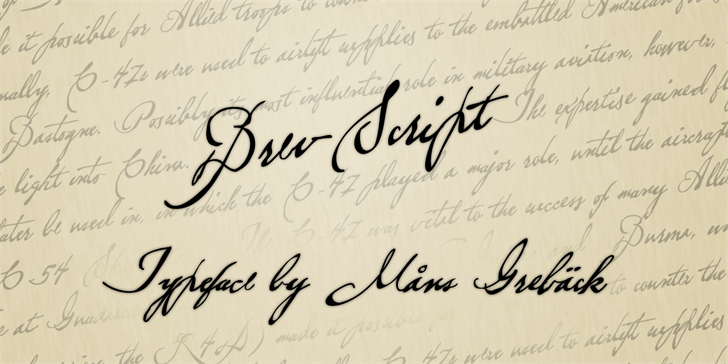
Brev Script font – Download Grátis
A Brev Script é uma fonte script que traz um tom alegre e vibrante para qualquer projeto gráfico. O designer Hamilton criou essa fonte com inspiração nos traços delicados dos dotes artesanais de época, incorporando-os num design moderno e dinâmico que se adapta perfeitamente a diversas aplicações. Esta fonte é ideal tanto para títulos quanto para textos mais subtiles, proporcionando um grau de personalização único. A sua natureza fluida e elegante faz dela uma escolha adequada para qualquer projeto que deseje dar um toque sofisticado à sua identidade visual. Visite o site www.mansgreback.com/brev-script para adquirir uma licença comercial desta fonte incrivelmente acessível e criativa. A Brev Script é mais do que apenas outra fonte; ela é uma ferramenta de design poderosa, perfeita para quem quer dar vida aos seus projetos com um toque único e agradável ao olho.